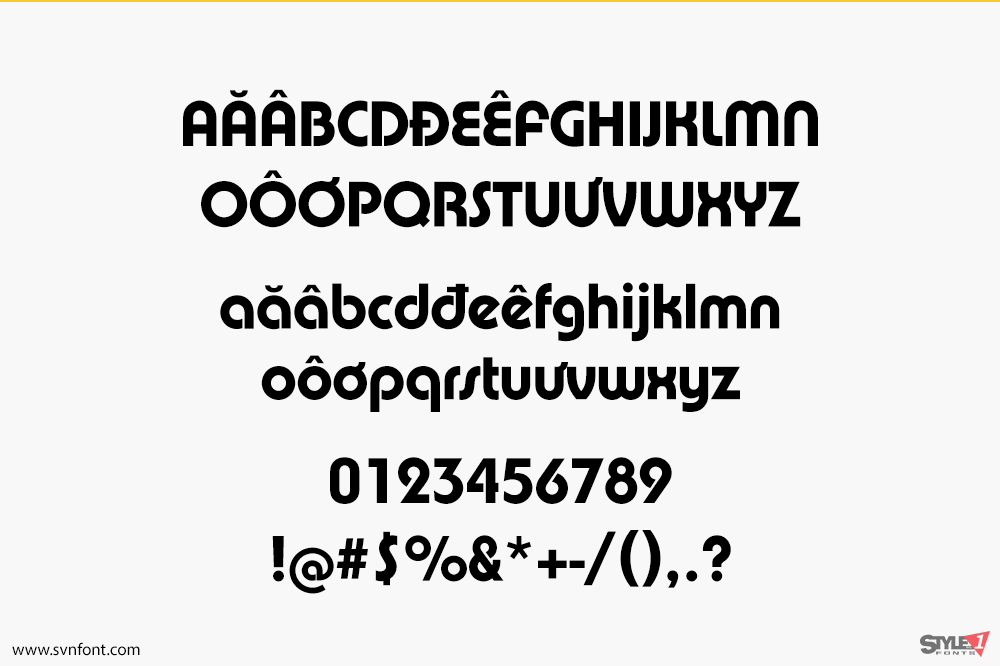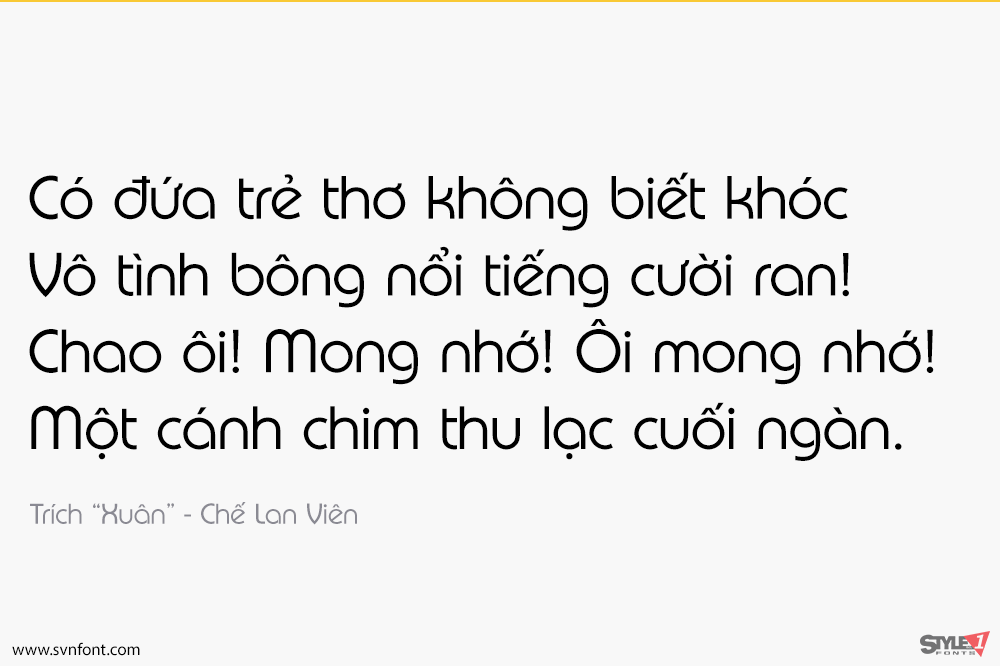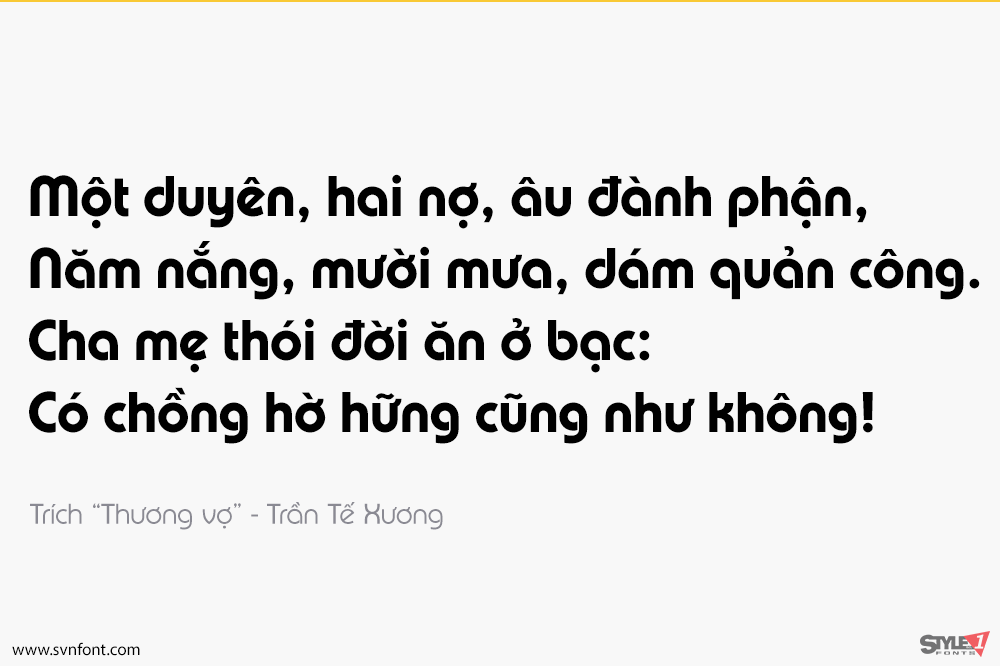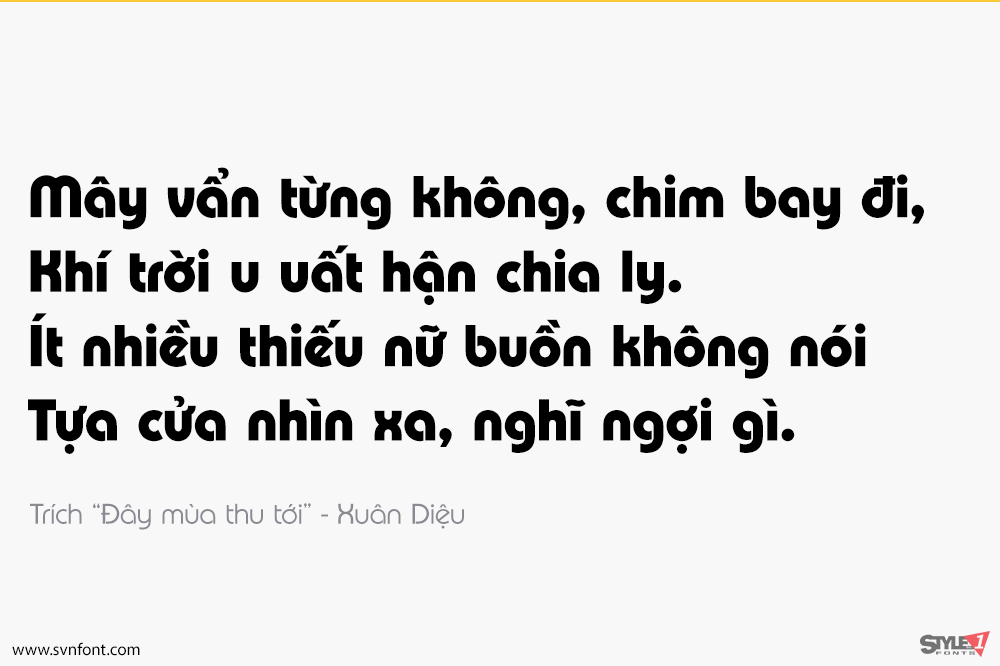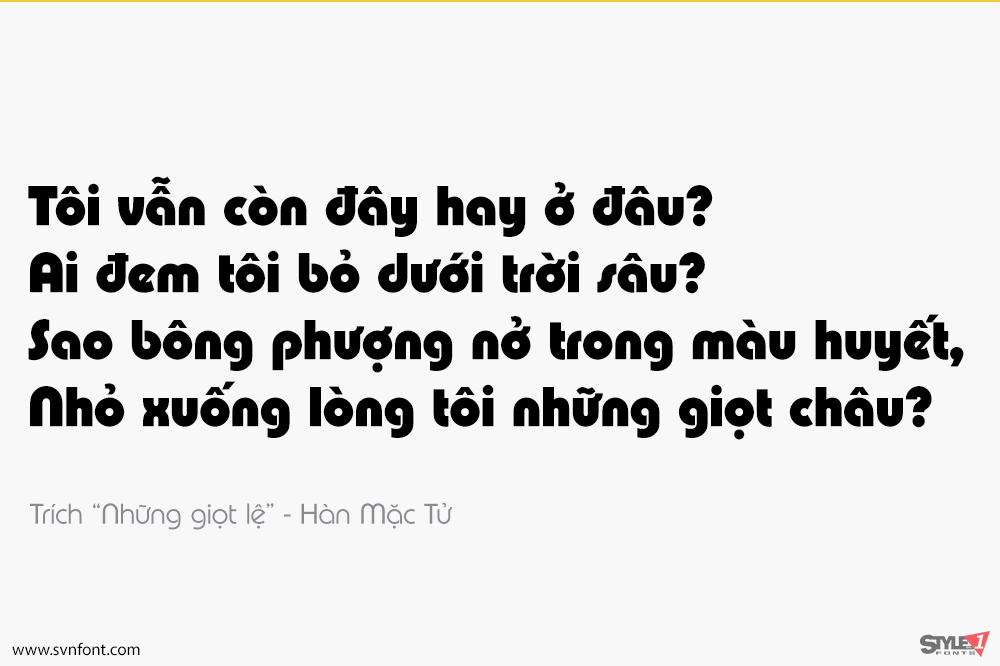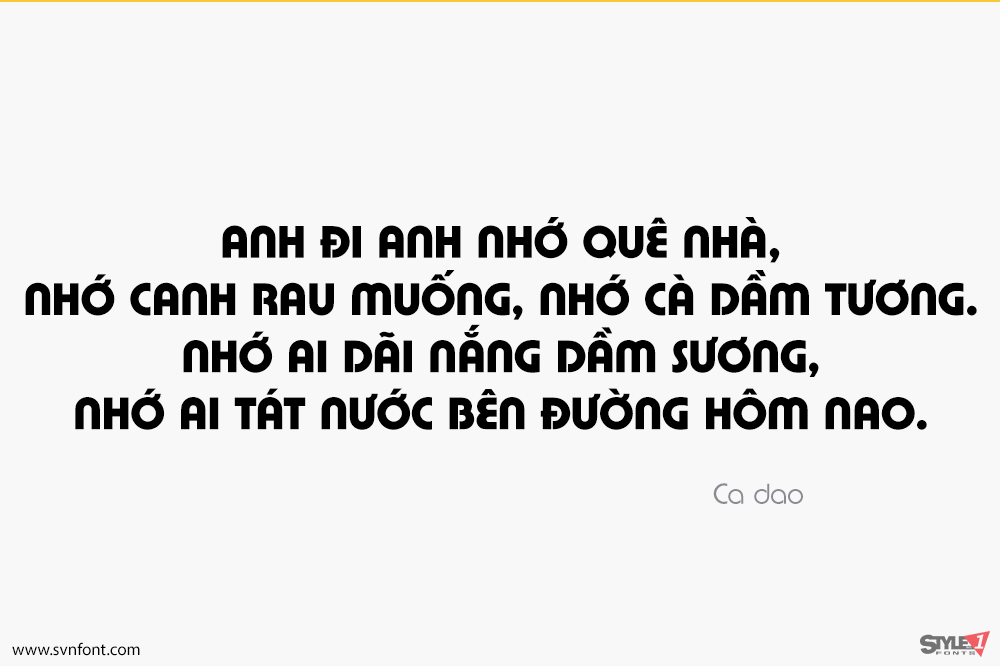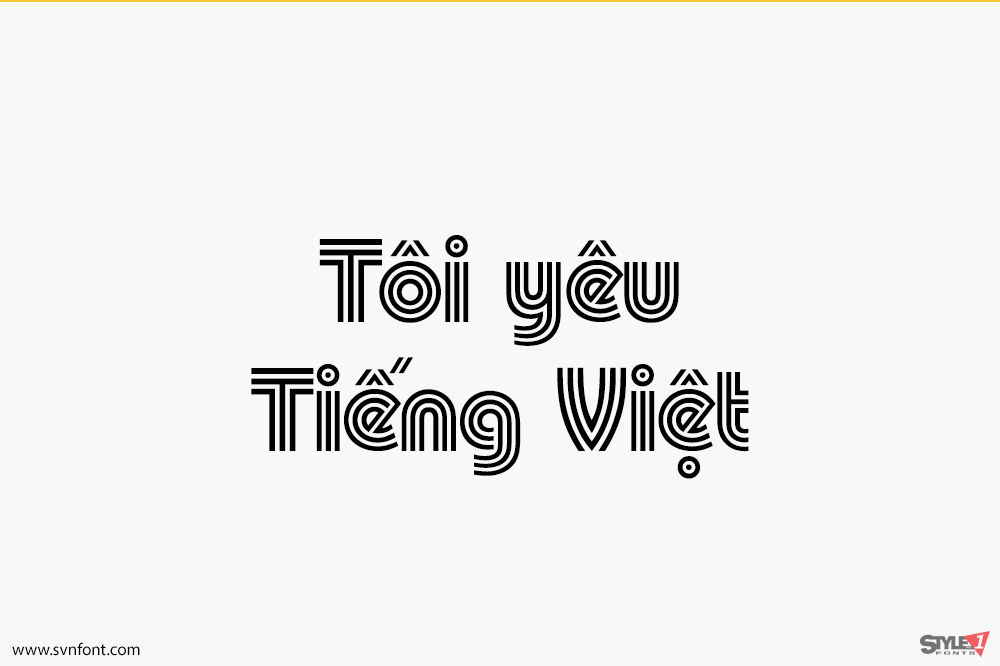
Pump – một typface vận dụng nhiêu nhữn nét uốn cong mạnh mẽ, tạo nên kiểu chữ tròn trịa và đáng yêu. Bộ font có 5 styles từ nhạt đến đậm, có một style là dạng Inline. Font thích hợp cho tiêu đề, logo, banner, menu,…
Nhà thiết kế: Philip Kelly
Nhà phát hành: ITC